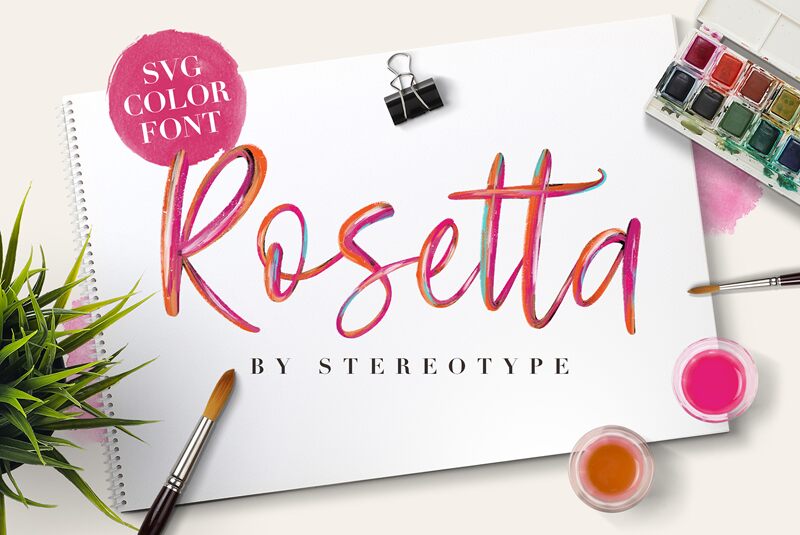
Rosetta Black è un carattere TTF classico. Funziona come qualsiasi altro font.
Rosetta Color è un esempio della versione a colori. Richiede Photoshop 2017 e/o Illustrator 2018 per funzionare. Funziona allo stesso modo di qualsiasi altro font, ma è composto da colori!
La versione commerciale contiene un'ampia serie di glifi alternativi e legature contestuali per creare il tuo stile!
Rosetta Color